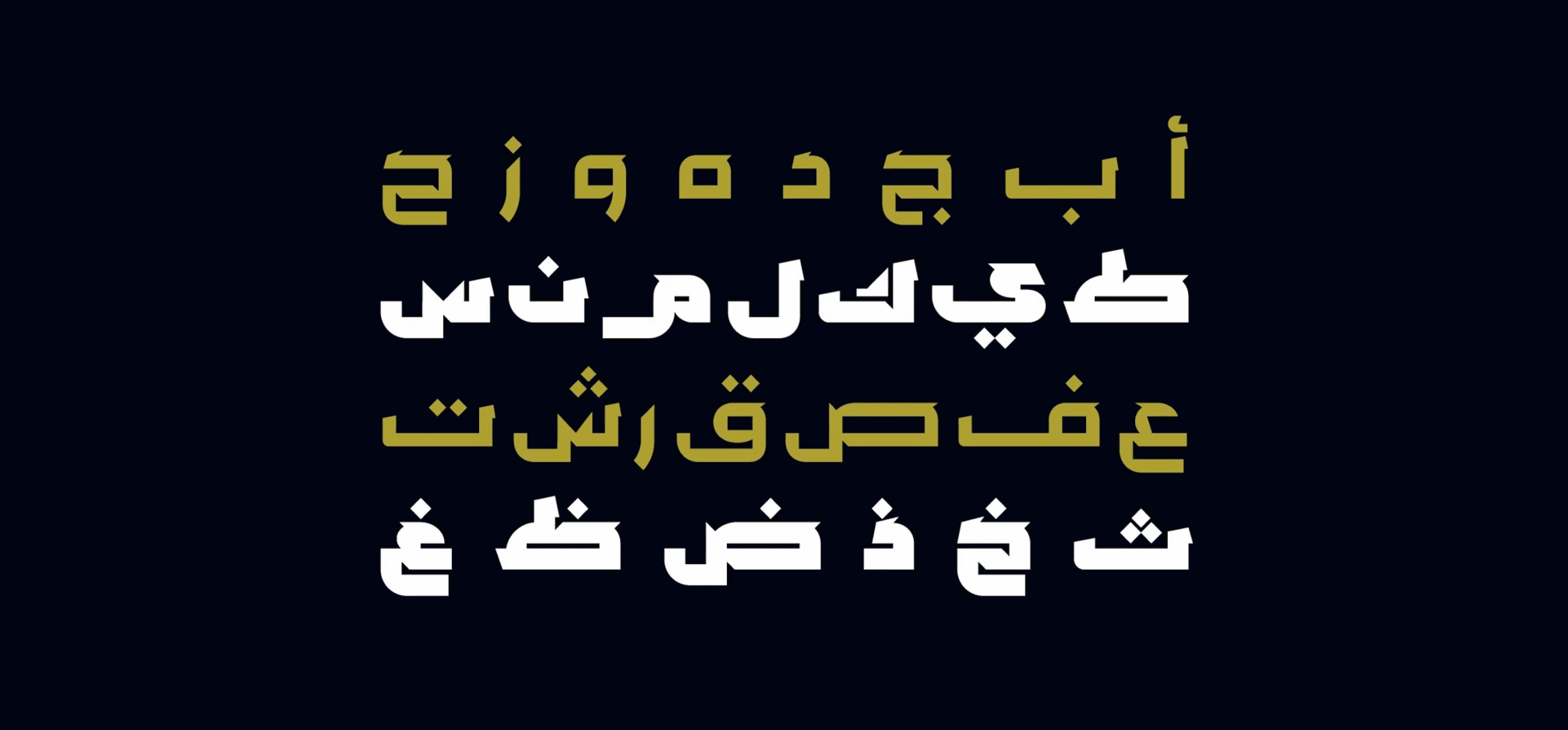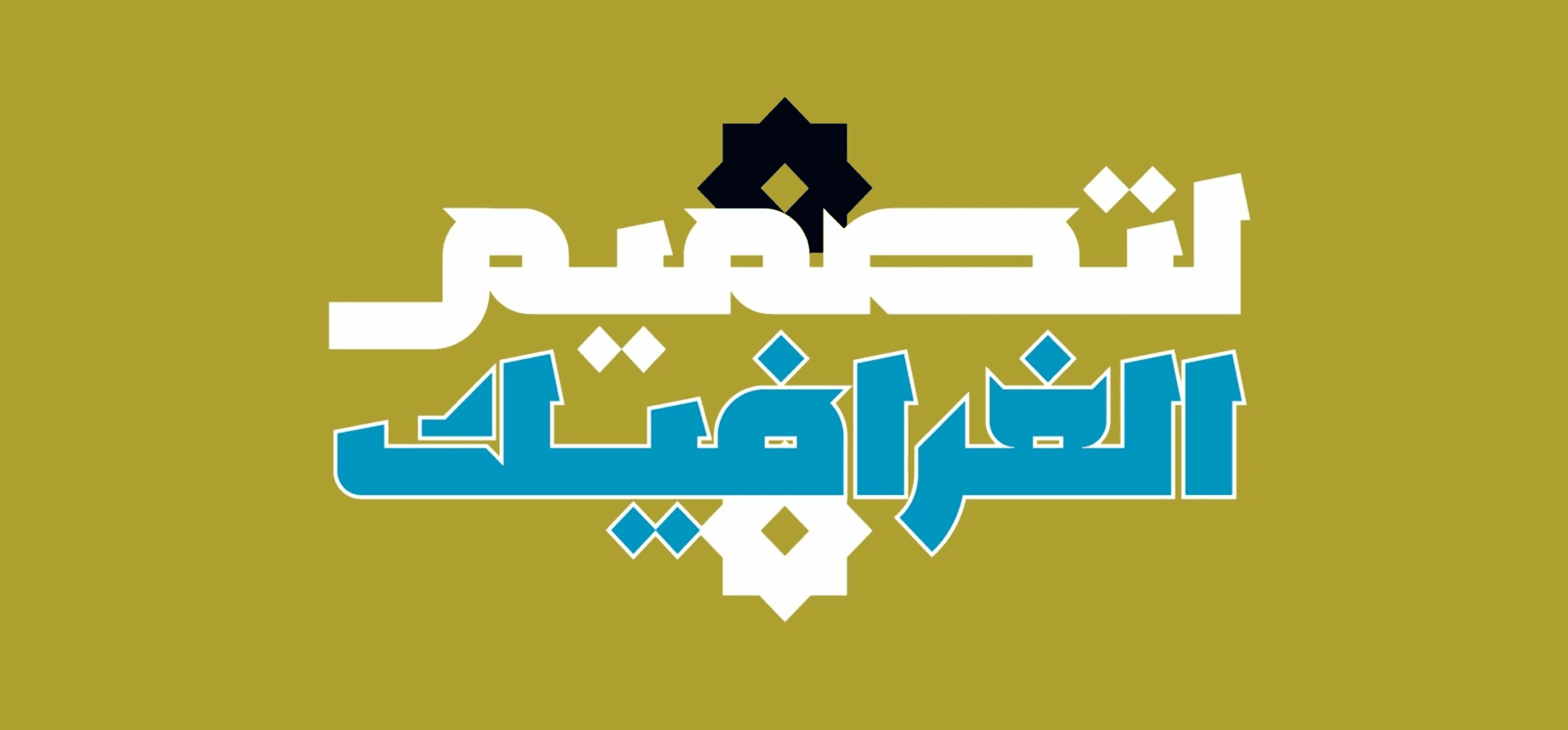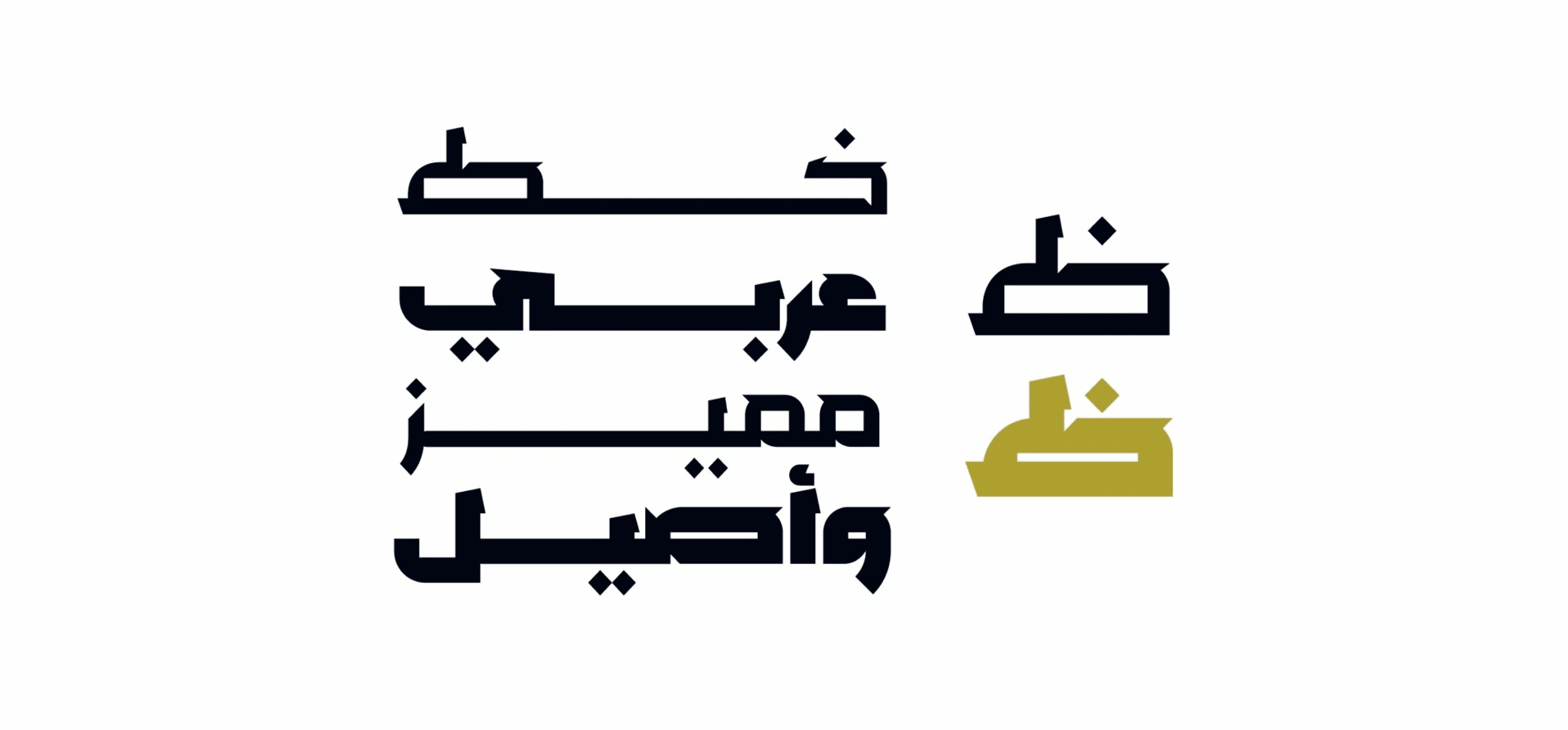
خط Mozhel (وهي كلمة عربية تعني "مُذهِل") هو خط عرض عربي يجمع بين أصالة الخط الكوفي القديم وبساطة التصميم العصري، ليقدم مظهرًا فريدًا يعكس التوازن بين التراث والحداثة. يتوفر الخط بوزنين: عادي (Regular) وعريض (Bold)، مما يجعله مناسبًا لمختلف المشاريع الإبداعية مثل تصميم الويب، المطبوعات، وتطبيقات الهواتف. كما يدعم أنظمة Windows وmacOS، ليمنح المصممين حرية استخدامه في بيئات عمل متنوعة.